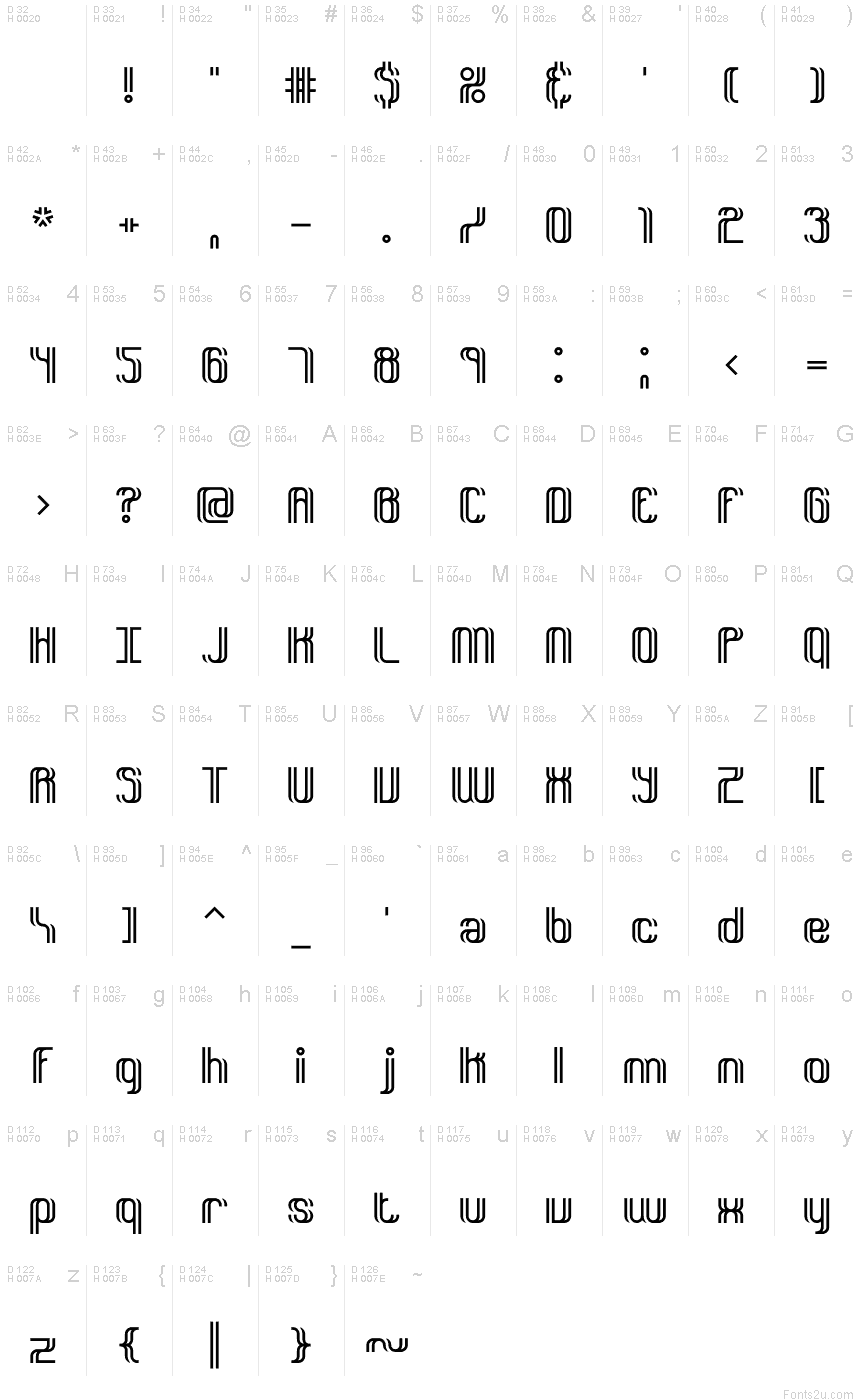
Dyphusion von ÆNIGMA FONTS ist eine kostenlose, groovige Display-Schrift, die an zu hohen, geschwungenen Buchstaben geformtes Neonlicht erinnert. Die ultrakondensierten Formen, die Doppellinien und die sanft abgerundeten Ecken erzeugen einen eleganten Retro-Futurismus-Rhythmus, der zugleich an Nachtclubs und Science-Fiction denken lässt. Dank der schmalen Proportionen lassen sich lange Wörter auch auf engem Raum platzieren, ohne dass der fließende, leuchtende Vibe verloren geht.
Mit Dyphusion verleihst du Postern, DJ-Flyern, Festival-Brandings, Album-Covern, Game-Titeln und Retro-Tech-Logos eine markante, elektrisierende Energie. Diese kostenlose Schrift glänzt besonders, wenn du den Begleittext in einer schlichten Sans oder einer geometrischen Grotesk hältst, sodass Dyphusion die auffälligen, plakativen Überschriften übernehmen kann.